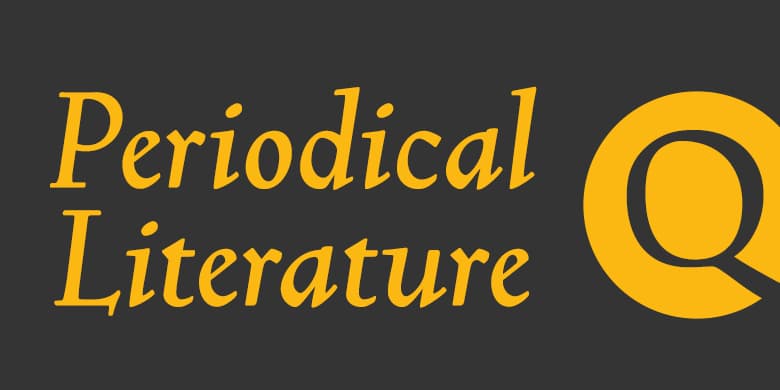
Truesdell™
Truesdell字体是基于Frederic W. Goudy在1931年设计的已丢失的字体。该基本字体是对热金属模板(hot metal matrices)进行的数字化。后来,为了丰富这个字体家族又增加了一些字符和字重。
The Truesdell font is based on the lost typeface designed by Frederic W. Goudy in 1931. The base font was digitized from hot metal matrices. Later, additional characters and weights were created to fill out the family.